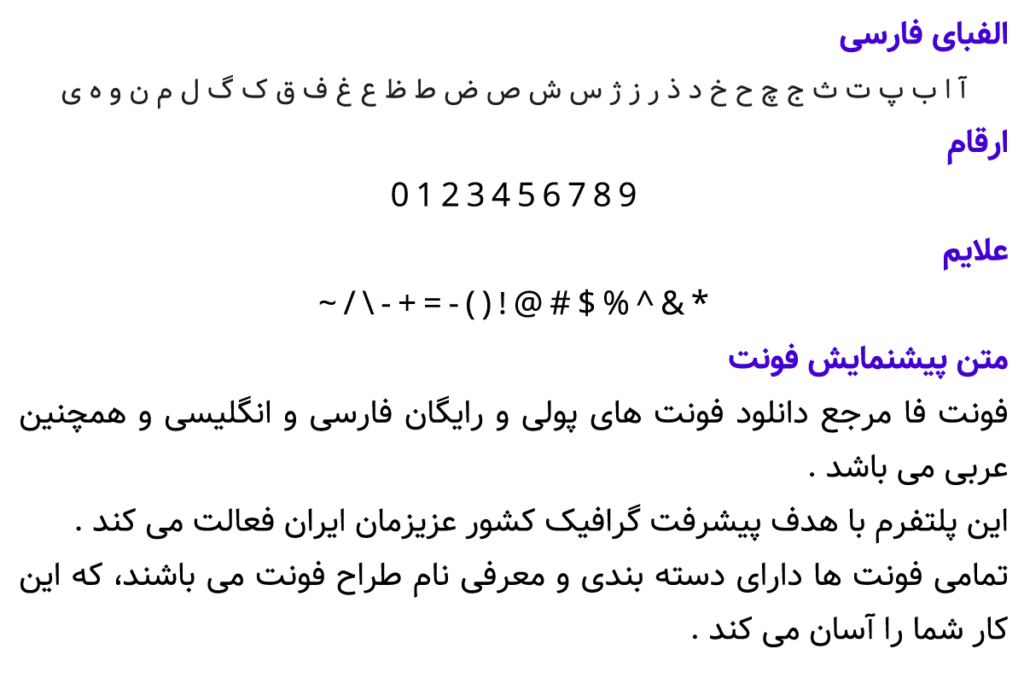
پیشنمایش فونت صمیم
فونت فارسی صمیم - Samim
توضیحات و معرفی فونت صمیم
فونت فارسی صمیم ( Samim ) از مجموعه فونت های آزاد می باشد، و نیز نوع فونت طراحی وب و عنوان و متن می باشد.
فونت خوشگل و زیبای مربوط توسط مرحوم صابر راستی کردار در سال 1394 شمسی طراحی و ایجاد شده است.
و نیز فونت صمیم در 3 وزن پر رنگ و متوسط و معمولی است.
• Samim Bold
• Samim Medium
• Samim Regular
نسخه های شامل حروف لاتین Open Sans، بدون حروف لاتین و تمام رقم های فارسی در بسته فشرده تایپ فیس موجود است.
شعر زیبای ایران وطنم که توسط این فونت نوشته شده است را در تصویر زیر نگاه کنید.